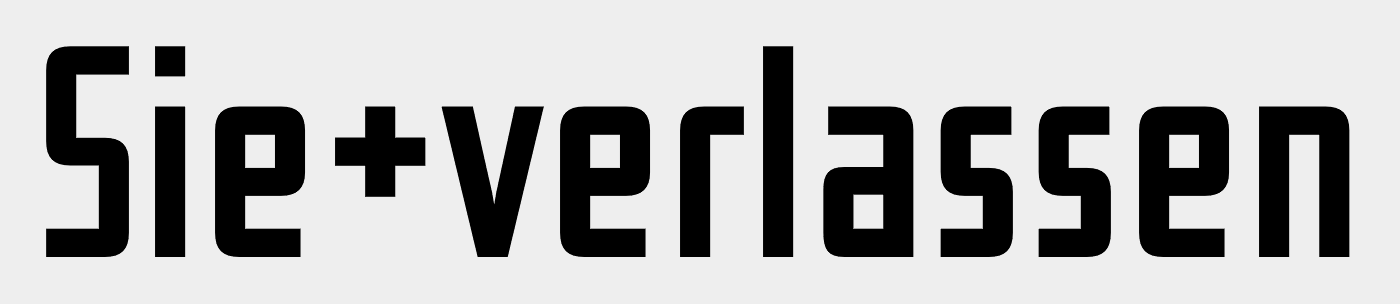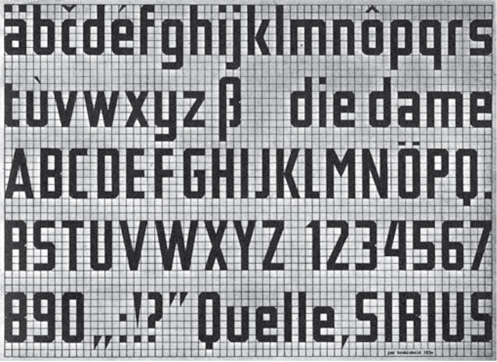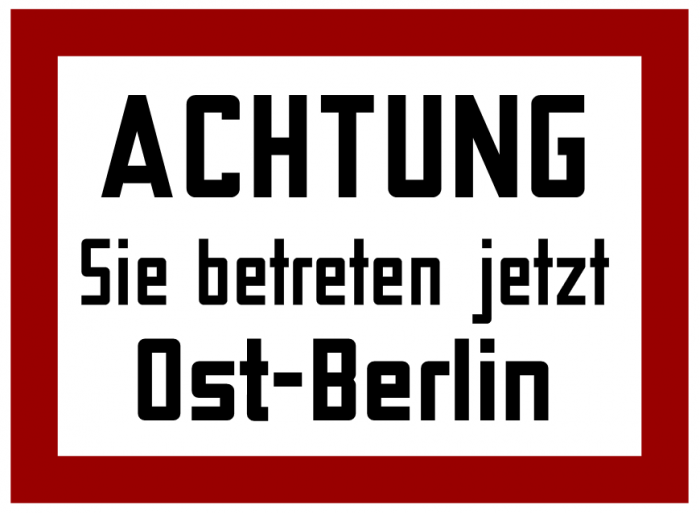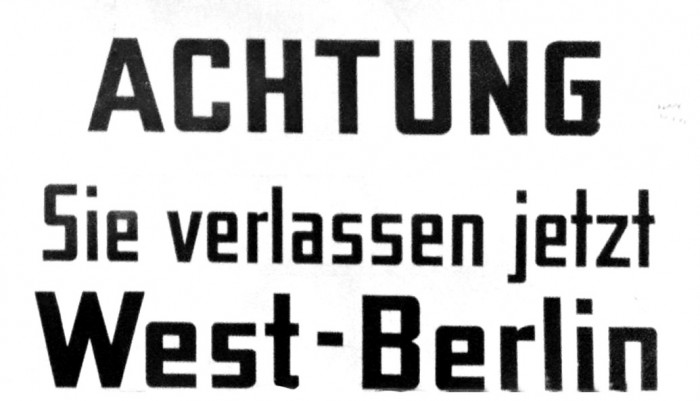
Historisches Schild an der Mauer
Aber generell hat es damals viele Handgemalte Hinweisschiler der Besartzungsmächte in der Nachkriegszeit gegeben, die such durch einen besonderen Stil auszeichneten, einfach weil diese von irgendwie im Schildermalen etwas geübteren Soldaten geschrieben wurden. Dieses  Schild hat einfach nur überlebt und wurde immer wieder renoviert, weil es eben an einer recht prominenten Stelle stand, ubnd die längste Zeit seiner Existenz eben durch das Faktische ad absurdum geführt wurde., Es war dort wohl am wenigsten möglich, dort West-Berlin zu verlassen, auch wenn rein rechtlicfh ein ganz schmaler Streifen vor der Mauer tatsächlich schon zu Ost-Berlin gehörte, eben so viel, dass von der Ostseite sehr zuverlässige Personen die Mauer neu streichen konnten, ohne sich schon, aus der Sicht der DDR, im Ausland zu befinden.
Hab schon viele gruselige Sachen von deiner schönen Seite, den ganze DIN 1451-Alptraum und so. Leider stecke ich nun in einer Sackgasse. Als Berlin rounded square bold condensed müsste man den Font oben wohl bezeichnen, wenn es denn einer wäre.
Zum Glück brauche ich ihn nicht konkret für irgendwas. Aber so eine Scheusslichkeit verdient unbedingt Beachtung.
Für die Versalien ist NORWESTER kein schlechter Ersatz.
Leider besteht er aber auch nur aus Versalien.
Ja, das stimmt schon. Besonders bei der Black kommen viele Überschneidungen in der Anmutung zustande. Vielleicht sollte man es dabei belassen. Danke
EDIT: Ich stelle gerade mit Erstaunen fest, dass die Tschichold-Vorlage der Iwan genau das zu sein scheint, was gesucht ist:
Dann schau noch mal genau; ich fürchte, du irrst in dieser Feststellung.
Hm … ich dachte, es geht um die Schrift auf dem Schild? Davon ist die ›Tschichold‹ nach wie vor sehr weit weg. Mit leichten Eingriffen wäre die Iwan Reschniev vollkommen ausreichend.
Was genau meinst du denn mit "sehr weit weg"?
Mit Peters Tschichold lässt sich das Schild astrein nachsetzen. Natürlich muss man dem damaligen Schildermacher ein paar Freiheiten zugestehen, aber das kann man ja nicht der Schriftvorlage anlasten, an die er sich ansonsten verblüffend streng gehalten hat. Ich habe mit wenigen Handgriffen sein C gemacht, bei dem er sich am O orientiert hat. Und die kleinen t wirken in Kreuzform autoritäter. Der Rest geht über Dehnen und Stauchen.
Die Iwan läuft sicher nicht schneller in das Sujet, zumal man sie erst kaufen und dann noch jedes e modifizieren müsste.
Es ist immer die Frage, was man sieht und was man übersieht. Für mich bestehen zwischen beiden Schildern erhebliche Unterschiede durch die unterschiedlichen Proportionen und einige Buchstabendetails in A, G, T, j, W, B, stark in r sowie durch das Strecken und Stauchen, das die im Originalschild annähernd gleiche Strichstärke im Nachbau ausschließt. Wer sich den Nachbau anschaut und nur einen leicht geübten Blick hat, sieht sofort, daß sie in die Breite gezerrt wurde. Aber wenn ich das am Anfang richtig verstanden habe, suchst du ja Scheußlichkeiten, und das ist das einzige, was ich auch für astrein halte.
Die Eingriffe beziehen sich ja nur auf das Schild. Darüberhinaus bin ich mit der Tschichold als Ausgangsschrift vollkommen happy. :)
Ist ja auch ne Frage, wofür man es braucht.  Will man richtig professionelle Drucksachen erstellen ist die richtig ausgefeilte Ivan sicher die bessere Wahl, Wird jedoch nur ein reines Privat-Projekt umgesetzt, sind Freefonts auch nicht falsch.
Ich hab noch ein wenig komplettiert, gekernt, eine weitere Version mit den alternativen C,c, f, t, y hinzugefügt, und hierzu dann einen fetten Schnitt für Achtung und West Berlin.
im Anhang Jan von Katz mit reparierten Scharf-s und einigen Änderungen in den Buchstabenweiten (ß, j, J) sowie wiederhergestellte Standardumlaute als Großbuchstaben (Ä, Ö und Ü). Das kann Peter ausschlachten, so er will und etwas Müßiggang pflegt.